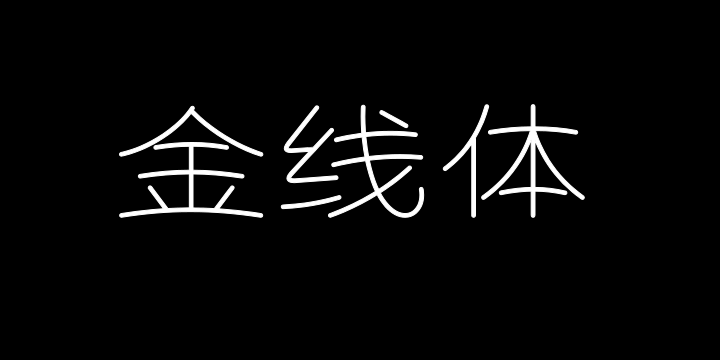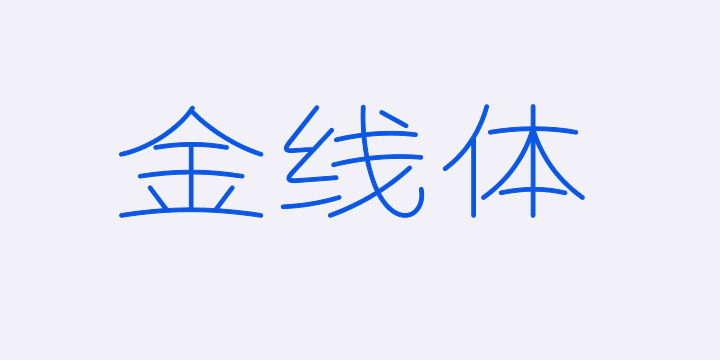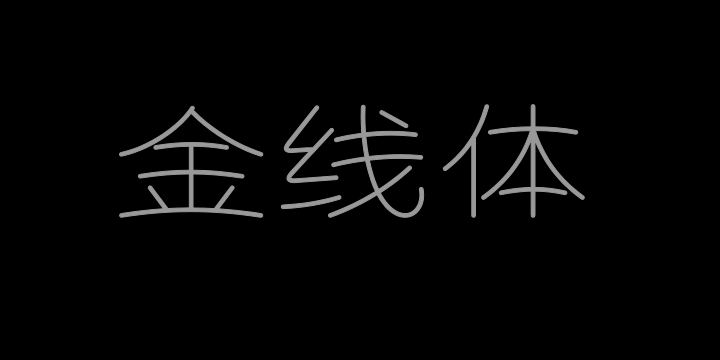
上首金线体 By 上首造字 商用字体
字体全名: 上首金线体
铸字厂: 上首造字
设计师: 胡博剑
字体简介: 上首金线体,简体中文约6763字。该字体的笔画纤细简约,粗细一致,字形扁圆流畅。较细的笔画使字面有大量的留白,让整套字看起来给人一种十分轻盈的感觉,却又不失美感。整套字体风格统一、特点一致,字体个性鲜明,具有艺术感,适用于搭配标志、广告标语、商业广告、海报字体等高端属性。